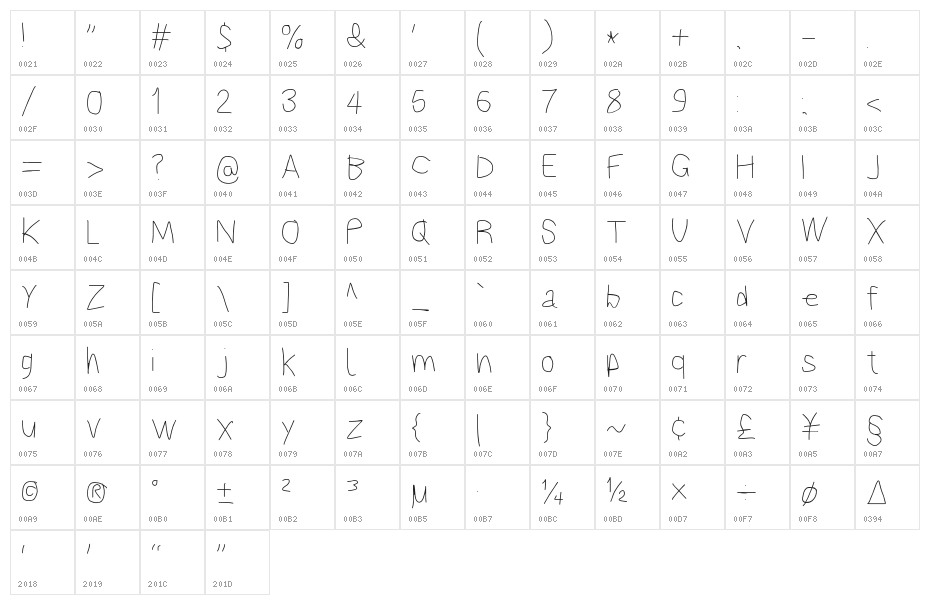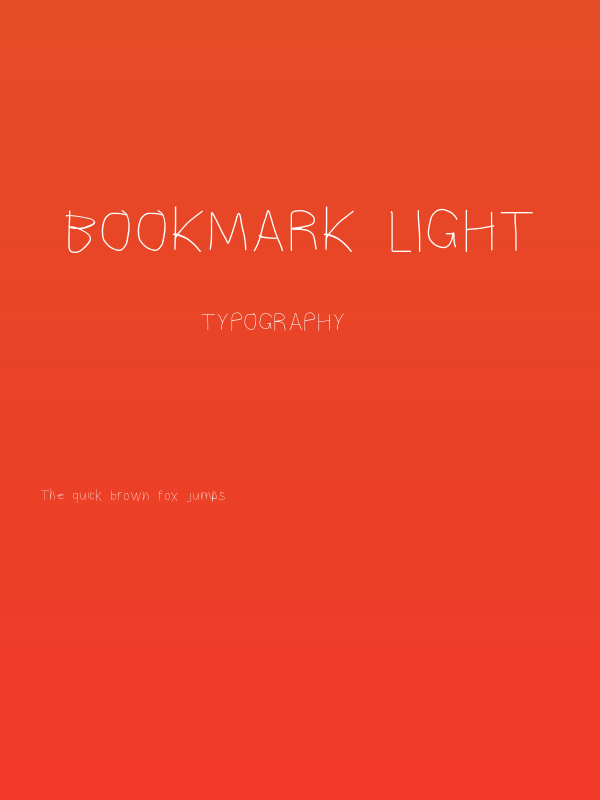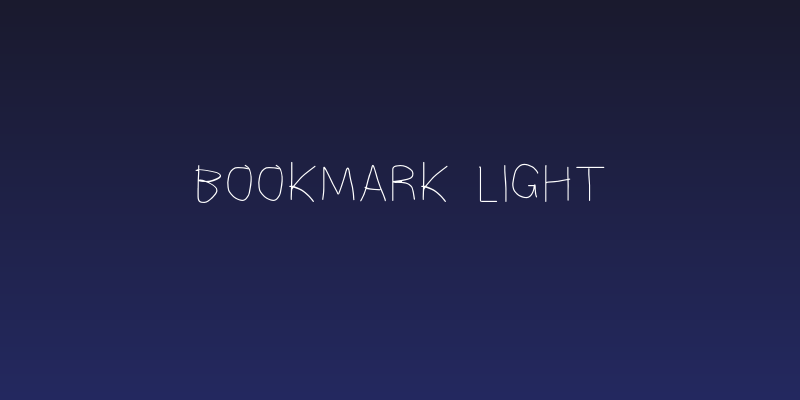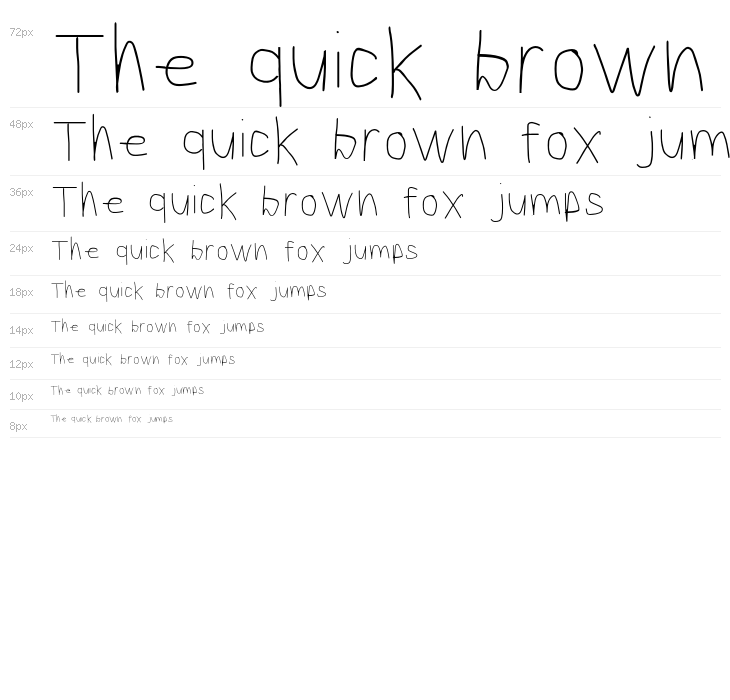
Bookmark Light Font
| Gesamtstil | Casual |
| Anwendungsfall | Greeting cards, Informal branding, Personal notes |
| Vorgeschlagene Projekte | Ideal for personal notes, greeting cards, children's books, and informal branding projects. |